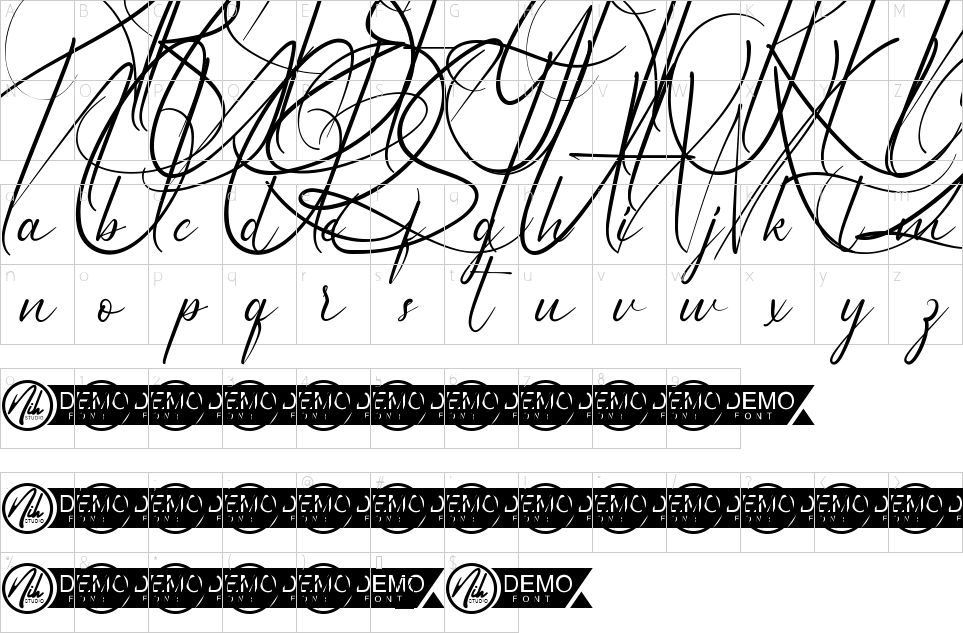
Amaya Signature Font – Download Grátis
A fonte Amaya Signature é uma opção elegante e sofisticada para aqueles que buscam uma maneira única de dar um toque personalizado a seus projetos digitais. Desenvolvida pelo nihstudio, esta fonte tem se destacado entre os usuários ao longo de sua disponibilização, sendo baixada mais de 7.225 vezes. A Amaya Signature oferece um estilo elegante e acentuado, perfeito para criações de branding ou design gráfico. Suavemente suave nas letras e linhas finas, a Amaya Signature se ajusta perfeitamente para gráficos profissionais e designers criativos. Se você está procurando por uma fonte com estilo único e de alta qualidade, a Amaya Signature pode ser a escolha perfeita para enriquecer seus projetos digitais.